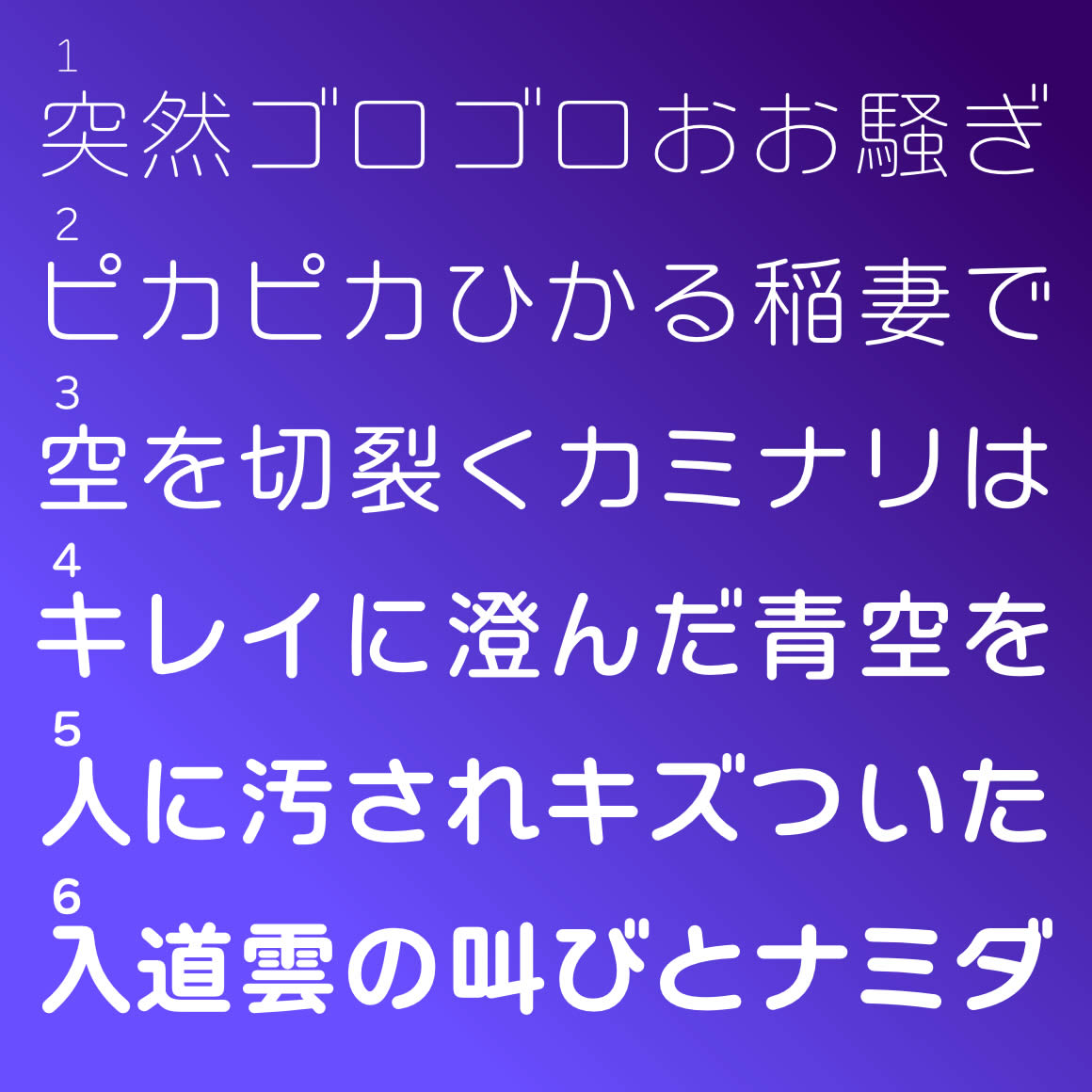
| デザイン |
水平垂直を意識して大きめにデザインされた、スマートな丸ゴシックかな書体「ニタラゴ丸」と、 プレーンなイメージの丸ゴシック書体「レラ」を組み合わせました。 スッキリとスマートな文字が、見やすさや読みやすさを向上させます。 等幅バージョンは、英大文字のアイ「I」と英小文字のエル「l」数字のいち「1」や、英大文字のオー「O」と数字のゼロ「0」が、はっきり区別がされているので、URL表記やプログラム編集などにぴったりです。 NEC特殊文字とIBM拡張文字も使えます。 |
連想されるイメージ 寄せられたコメントから抜粋 |
見やすい・そのままロゴに使える・すっきり・洗練されている・変なクセがない・曲線がキレイ・文字がうまく並ぶ・カッコイイ・オシャレ |